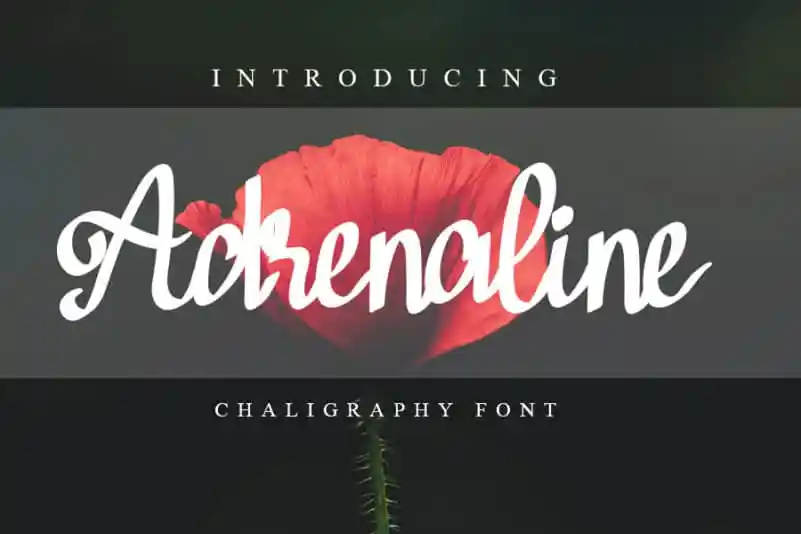
Adrenaline Brush Font – Download Grátis
A Adrenaline Brush Font é uma escolha perfeita para designers que buscam adicionar um toque inovador aos seus projetos digitais. Essa fonte manterá sua elegância tipográfica enquanto mantém um apelo contemporâneo e fresco, garantindo uma versatilidade excepcional. Ideal tanto para cartões de letra e títulos quanto para papelaria, a Adrenaline Brush Font atende a uma variedade de ideias criativas e pode realmente tornar qualquer projeto mais atraente e sofisticada. É perfeitamente adaptável para aplicativos variados como design editorial, branding, identidade visual e muito mais. E com seu designer inermediaSTUDIO, a Adrenaline Brush Font está equipada para dar um impulso brilhante em qualquer projeto que precise de uma mãozinha elegante e moderna.